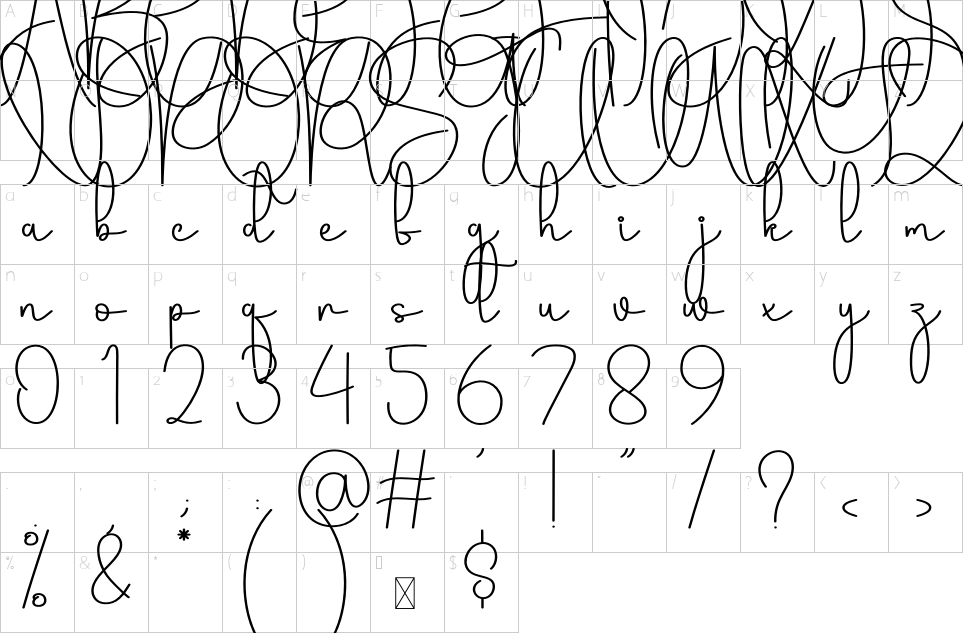
Magical Font | 1001 Free Fonts – Fonte Grátis
A Magical Font é uma fonte criada por William Jhordy, disponível gratuitamente tanto para Windows quanto para Mac. Esta elegante e moderna fonte é perfeita para qualquer projeto que valorize estilo e sofisticação. William Jhordy dedicou seu trabalho para criar uma fonte única que enriquece qualquer layout, seja para fins pessoais ou profissionais. A Magical Font já foi baixada 294 vezes, uma indicação do seu desempenho e popularidade. Seja para um projeto de escrita criativa, uma publicação de moda ou até mesmo para criar artigos de blog, essa fonte adicionará um toque diferenciado e sofisticado. Não espere mais para experimentar a Magical Font. Seu design único e funcional será uma escolha inteligente para qualquer projeto que você está desenvolvendo.